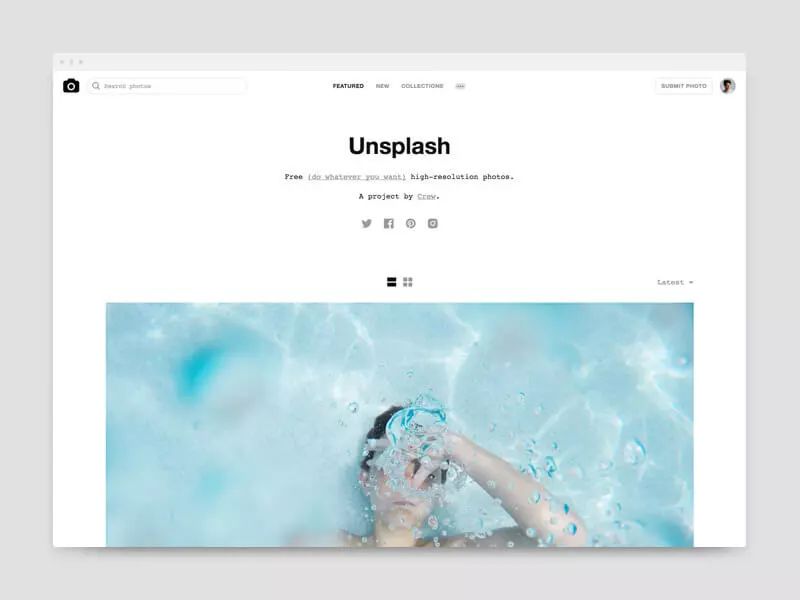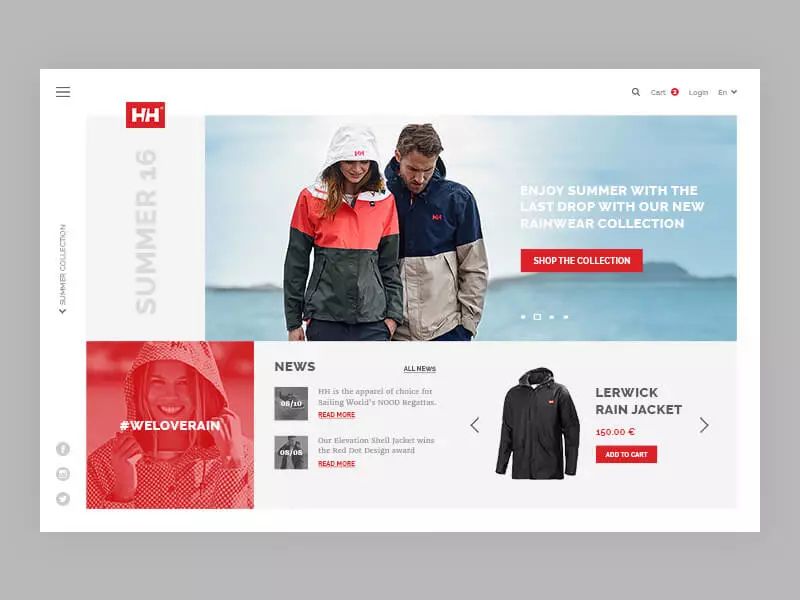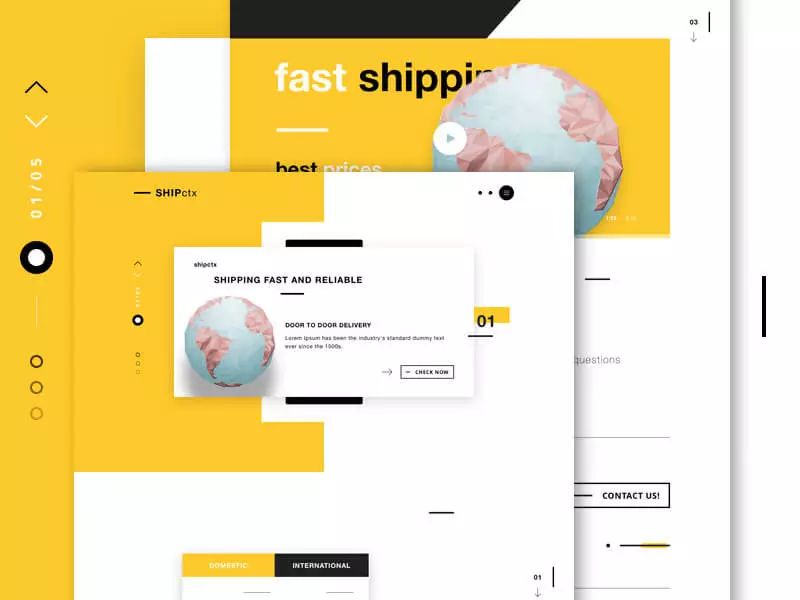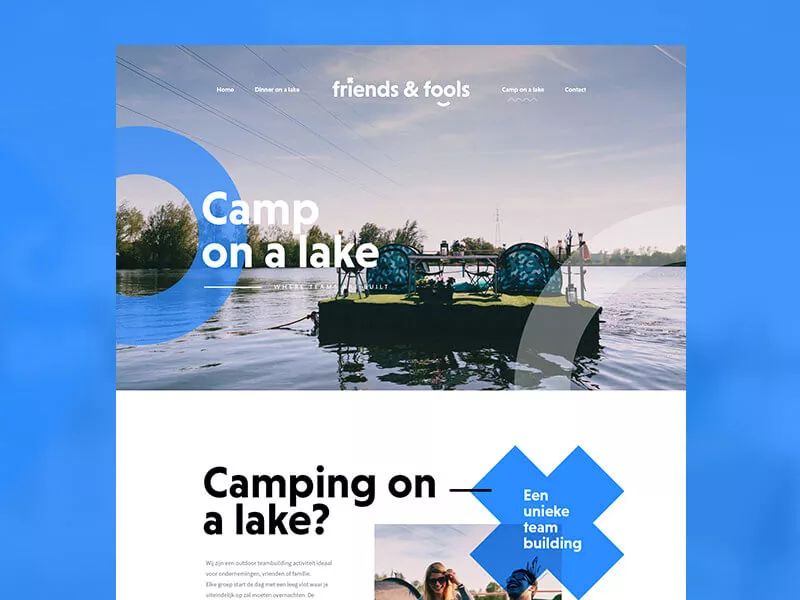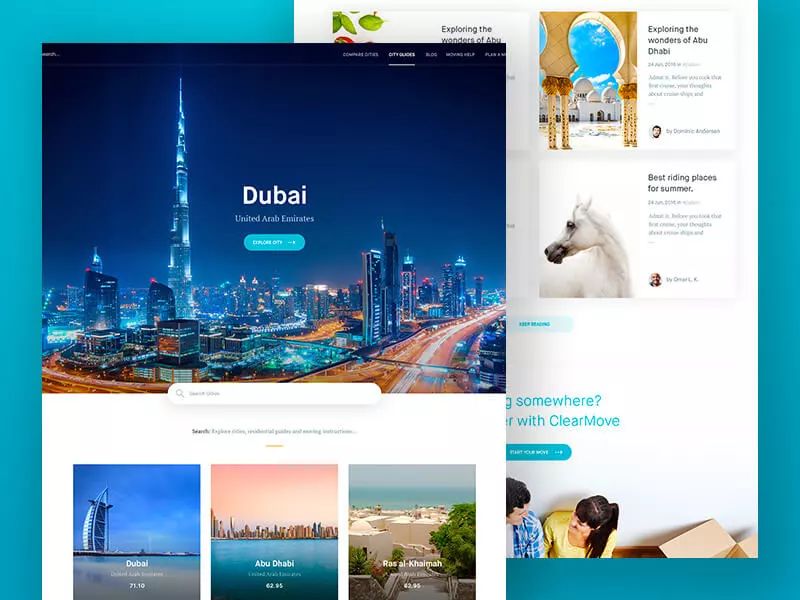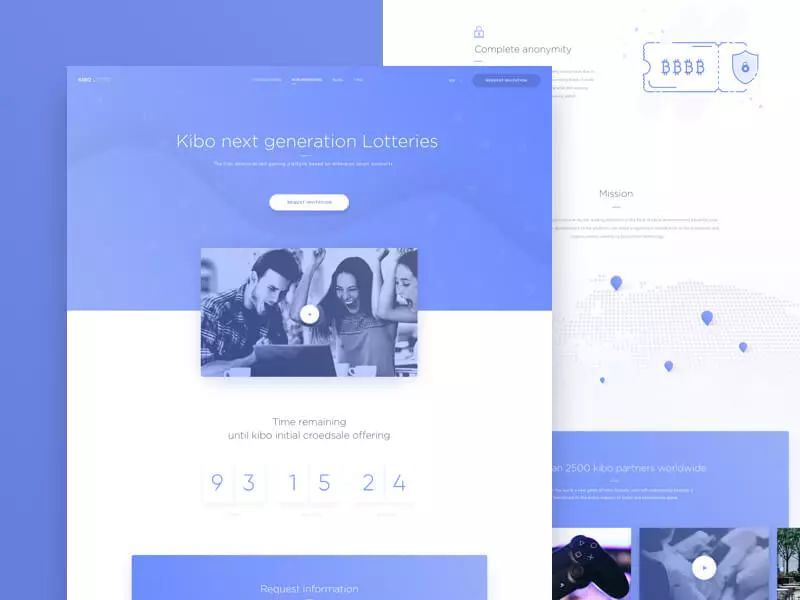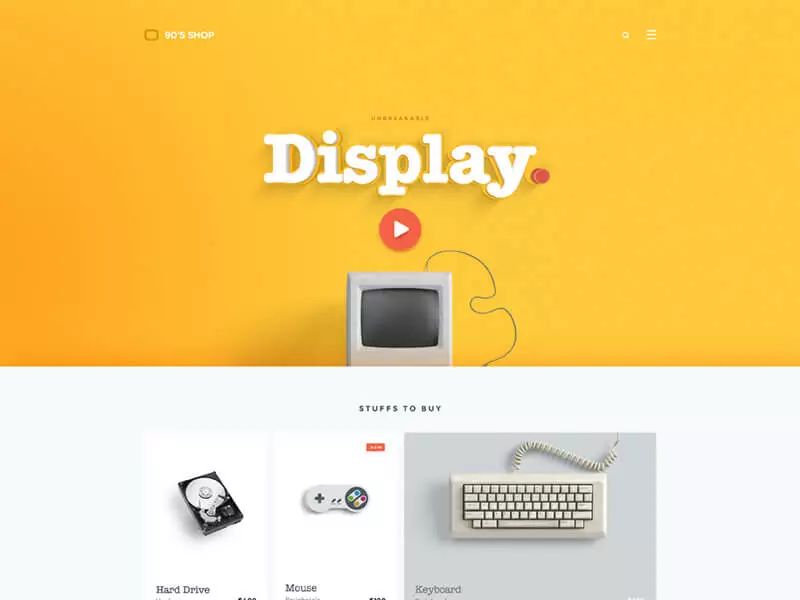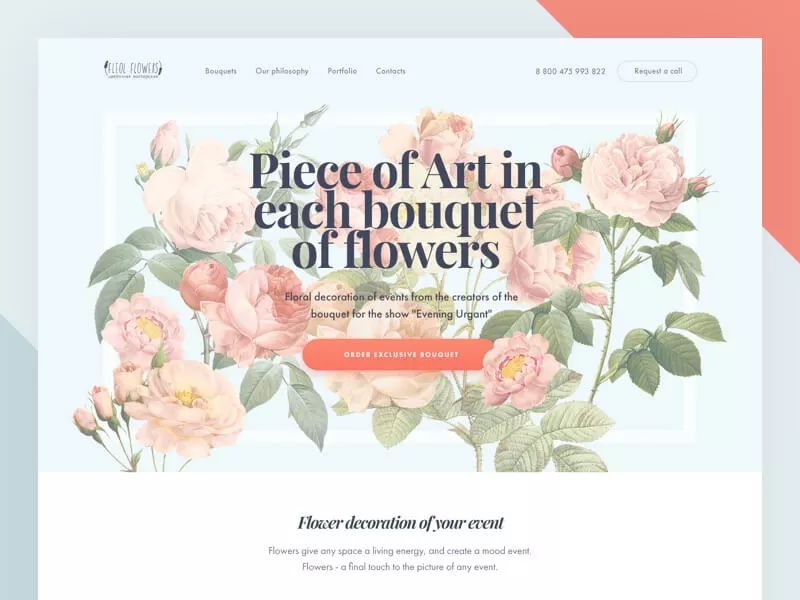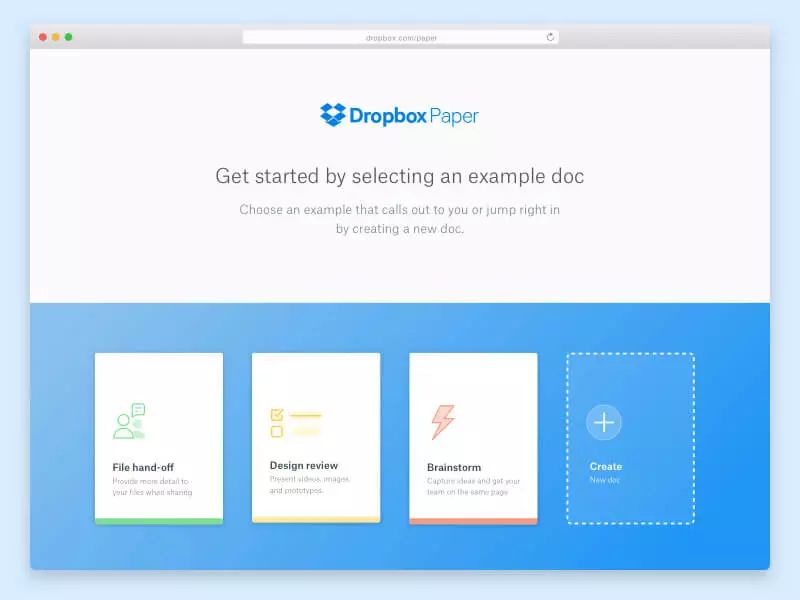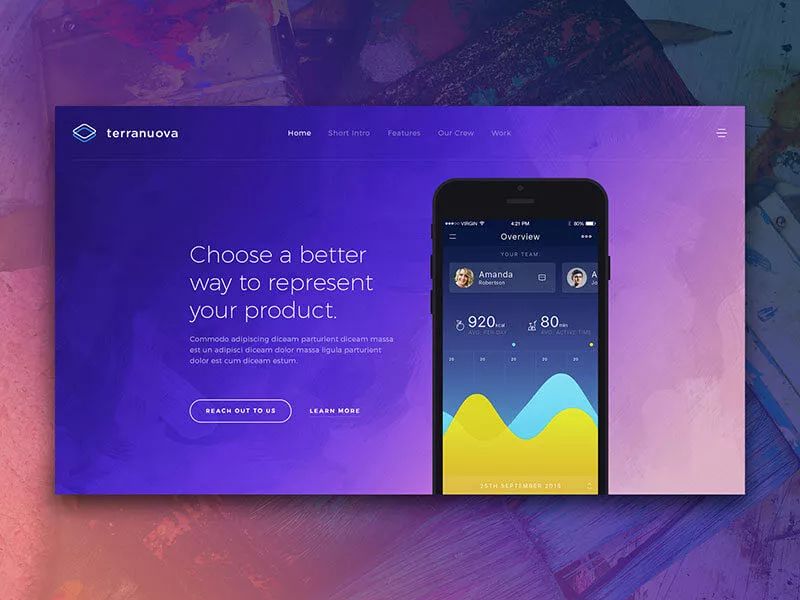
想提高作品层次感?先学会这12个字体运用技巧!
字体视觉上的层次感(英: Visual Hierarchy),究竟意味着什么呢?
因为对设计项目有着致命的影响,所以我们需要好好的研究讨论。当你这样做了,我们可以让用户很方便的了解到你所想要引起注意的要点,让说明变得通俗易懂。
在没有利用阶层的情况下,文字、单词或文章看上去都差不多,用户想要获取对他有用的信息是非常困难的。
那么接下来,我将会为大家介绍,如何使用文字的阶层效果,来让用户方便的获取到他所需要的信息,制作出充满魅力的网站。
文字是设计素材的一部分,有意识的思考特定的构造组合是有必要的。首先,文字有着什么样的意思,我们需要仔细思考运用是否得当。
大小
这是最能将设计要素强调的技术。人的视线自然会被那些大的东西所吸引,文字如果使用大尺寸的字体,用户自然就会去阅读那些内容了。
缩小字体,让他与其他字体不同,仔细调整是很有必要的。在你使字体变大或者变小的时候,他并不会完全按照我们的预期变化,你需要时刻保持着细心。(例如你在使用装饰性的字体的时候)
字体大小没有统一感,会有种非常业余的感觉,也会让文字变得难以阅读,尺寸的调整也会变得不可能。下面这个样本使用了Open Sans这个字体,这样优雅的字体用在标题这里是再合适不过的了。【Open Sans是一个由Google委托Steve Matteson设计的无衬线字体。根据Google的说法,它是以“诚实的重要性、开放的表现形式、及一个中立但具亲和力的外观”的理念设计的,并且“针对打印、互联网、行动设备的可读性所最优化。” 】
在调整字体大小的时候,你需要验证这个大小是否合适。首先从正文而不是标题开始,先确定他们的主字体。将字体的特点引发出来,让用户看到有魅力的效果。
调整字体大小需要注意的几点
正文用的字体大小,最好在14pt以上。(19px)
标题大小,最好控制在35pt以下。(约为正文的250%)
小标题的大小,最好控制在25pt以下。(约为正文的175%)
导航菜单的大小,最好控制在23pt以下(约为正文的165%)
导航菜单上的字符大小,最好控制在20pt以下(约为正文的140%)
重量
文字的重量,就是指文字的厚度,以及该留出多少空白空间的意思。明显和尺寸的重要性不同,特别是采用了独特的字体时,可以更加突出一些重要内容。
一旦你决定了文字的尺寸和重量,接下来就让我们想想该使用什么字体吧。粗体和细体一起使用,可以很好的表现出层次感。为了传达出文字的重要性,有一个非常著名的设计方法,就算是小屏幕画面状态下也能将文字表现出来的技术。
斜体
斜体也是非常有效的强调手段,有时也比粗体更容易引人注意。因为视觉差异比较小,对特别的字体是十分有效的。
小写还是大写?
所有的文字都使用大写,有人会这样主张这样可以起到令人震惊的效果,对于网页设计来说也是同样的。在项目中使用大写,就可以增强层次感,可以防止字号小的文字与背景互相混合在一起。
配色
文字的重量也依赖颜色,让我们来制作一个易于使用的配色方案吧。因此我们需要学习一些美术的基本原理,例如冷色与暖色的不同,流行色与自然色等,学习一些配色的基本原则是非常重要的。
将配色应用到文字上时,也需要注意他的层次感。使用明亮鲜艳的颜色,则表明他比其他的元素都重要,你需要知道一些颜色和对比相关的一些知识。
对比
如同字面意思一样,对比能在配色、重量、尺寸等各种各样的地方使用。正文与标题的对比,可以说是最常见的技术了。
留白
在文章的段落和文字之间留下空白的空间,可以很好的提高阅读效果。但因为有需要调整字符宽度,所以使用时需要小心。
首先第一个需要考虑的便是行距,不同的尺寸与颜色,我们需要选择合适的风格。
使用了留白之后,因为也会影响到阶层的顺序,如果是使用了风格相似的字体,留白能稍稍降低他们之间的关联性,创造出让人耳目一新的效果。但是,如果有想让人注意的部分与别的文字做比较,你需要仔细的调整他们之间的平衡性。
方向
方向(英: Orientation),就是指在布局中文字的表现形式。虽然看起来是显而易见的事,但在层次表现上却是一个重要的过程。在大多数情况下字母与数字,在屏幕上以水平直线放置,这样会整洁易读。
如果文字垂直放置,不仅会成为重要的设计要素,所有的视线也都会被集中在上面。尽管这种技术能扭转你的设计,但作为设计师,你还是需要充分理解自己的设计意图后再去使用。
质感、纹理
文字的纹理质感,是需要花费大量时间来掌握的一种技术。这种难,并不是指字体自身的质感,而是指在页面上所有文字的样式。使用合适的纹理,变化设计的元素,打破原有的设计规律吧。明确意图或概念,让你的设计不会矫枉过正。
层级
不管是怎样复杂的项目,都可以利用文字来分成三层,将网站上重要的部分完整的区分出来。这里的利用的阶层分为:主层(英: Primary)、副层(英: Secondary)、三层(英: Tertiary)。
主层(英: Primary)上的文字,是页面上最突出的元素。一般会使用大尺寸和鲜艳的颜色来使用,表现出与其他文字不同的魅力。但是,因为文字对层级的影响过多,使用会有限制,例如只在标题中使用。
副层(英: Secondary)上的文字,并没有主层那样的影响力,却能很好的让用户的注意力转向正文的内容。利用配色、尺寸、留白等这些不同的要点,区分主次,可以用在小标题,导语和摘录上。
三层(英: Tertiary)上的文字,是利用在主要内容上的,没有什么特点的要素。在这里使用的字体并不需要多么的引人注意,可以选择一些简单的,没有什么浮夸的效果的字体。不要干扰到主要内容,从而让用户的视线转移到别的地方。